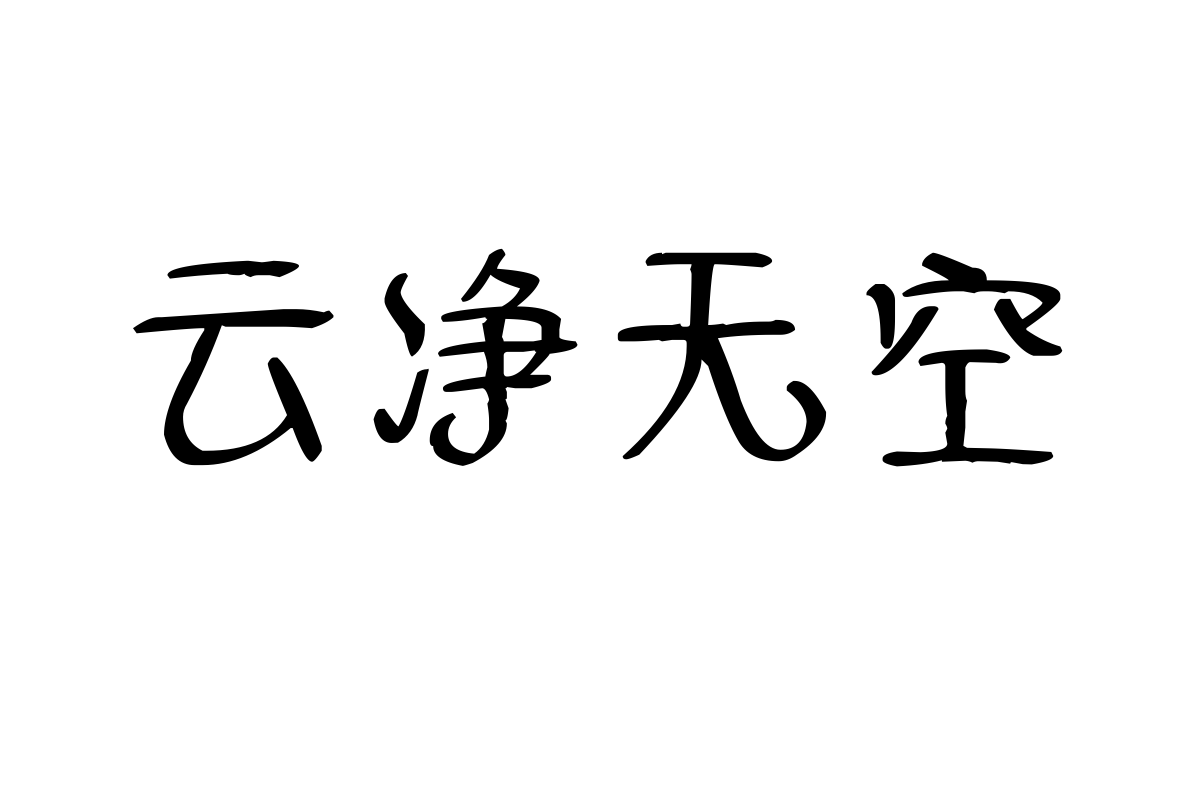
蝉羽爱情物语是一款具有独特设计感的字体,它采用了流畅而优雅的笔触,使得整个字体看起来既自然又富有艺术感。这款字体特别适合用于各种与爱情相关的主题,如浪漫、爱情、友情等,能够为作品增添一份独特的魅力。
蝉羽爱情物语的字形结构简洁明了,线条流畅自然,给人一种轻松愉悦的感觉。它的笔画粗细适中,既有力量感,又不失柔和,使得整个字体看起来既稳重又充满动感。此外,蝉羽爱情物语还注重细节的处理,每个字的间距和角度都经过精心调整,使得整体效果更加和谐统一。
总的来说,蝉羽爱情物语是一款非常出色的字体,无论是在视觉上还是情感上都能够给人留下深刻的印象。无论是用于个人作品还是商业用途,都值得一试。